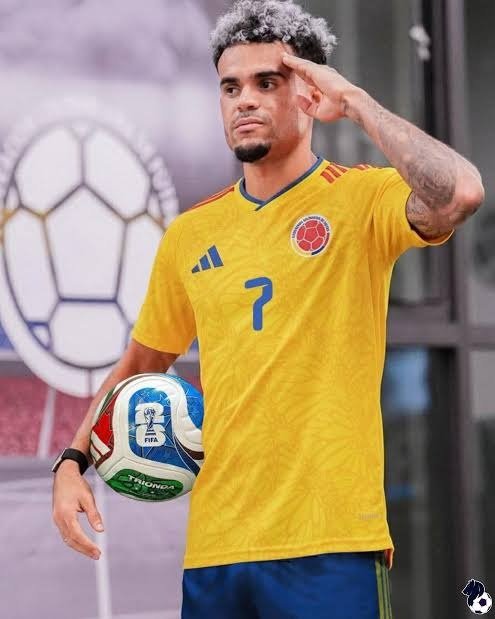
Tipografía Números Fuente Camisetas COLOMBIA - MUNDIAL 2026
Tipografía Números Fuente MUNDIAL 2026
Tipografia Colombia 2026 Mundial Camisetas Ttf Dorsal Números